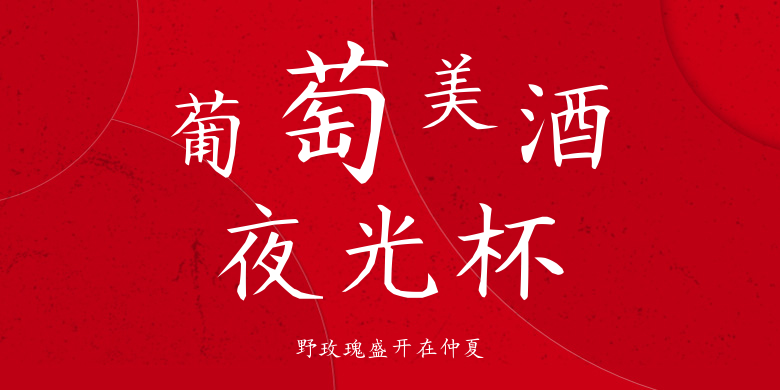
野玫瑰盛开在仲夏
野玫瑰盛开在仲夏,这款字体结构工整、笔画清晰,兼顾美观与易读性,适用于标题、正文、海报、包装、LOGO 等多种场景。字形优雅稳定,风格百搭耐看,适配日常排版与创意设计,让文字呈现更舒适、更具质感。野玫瑰盛开在仲夏一笔一画,皆是细节,以均衡的比例、流畅的线条打造舒适视觉体验,字形端正大气,风格简约现代。无论是商业设计、品牌宣传还是日常排版,都能轻松驾驭,让文字更有格调与力量。野玫瑰盛开在仲夏字体下载。